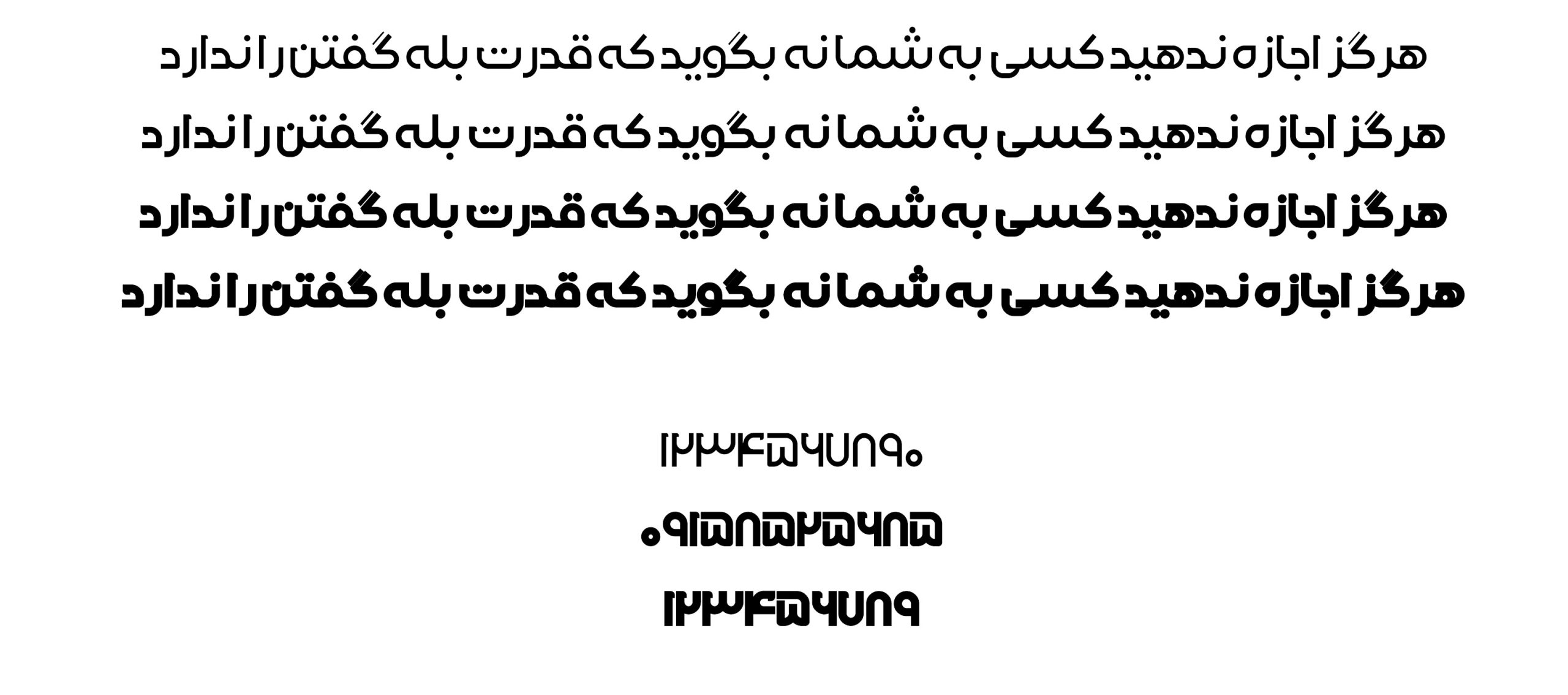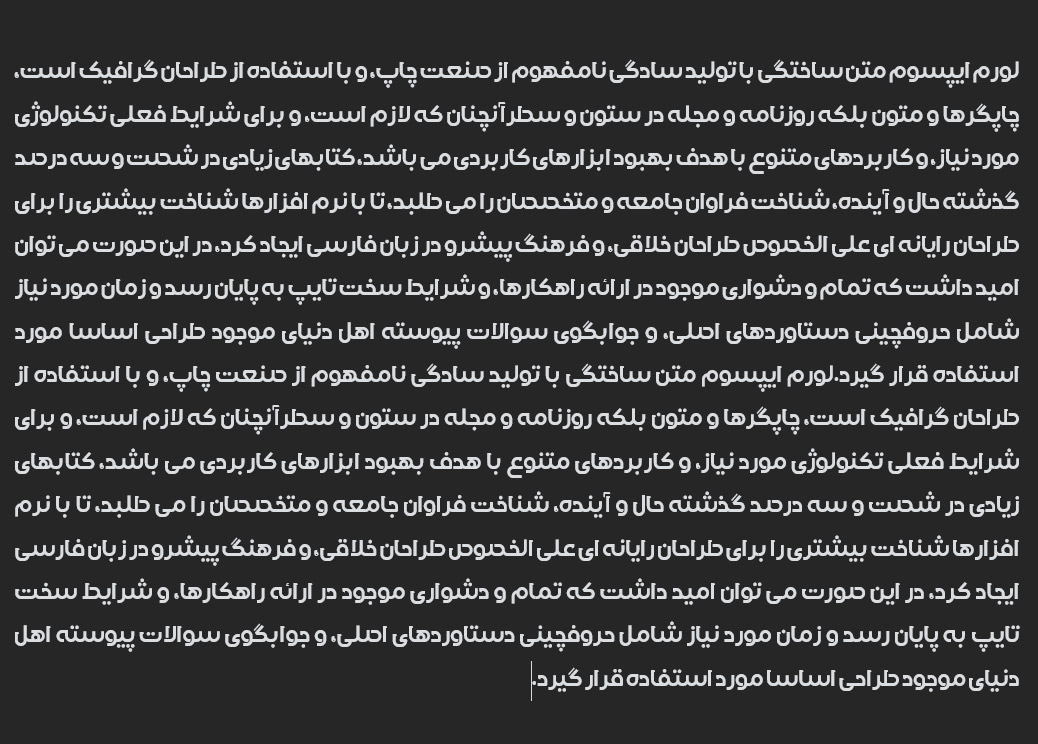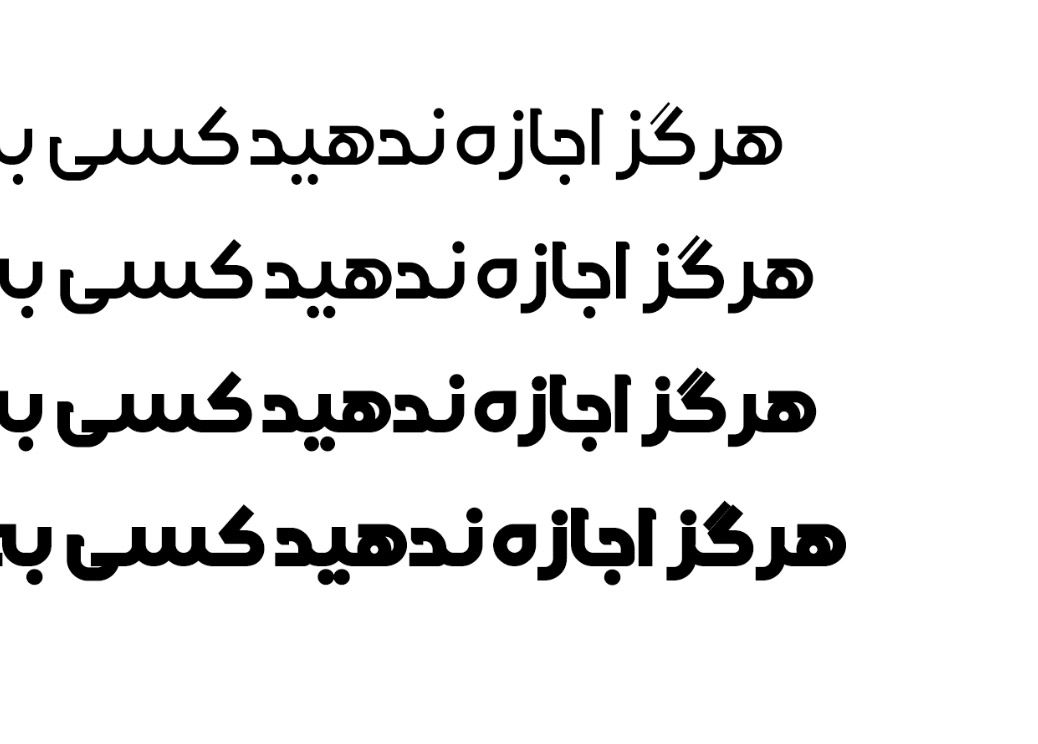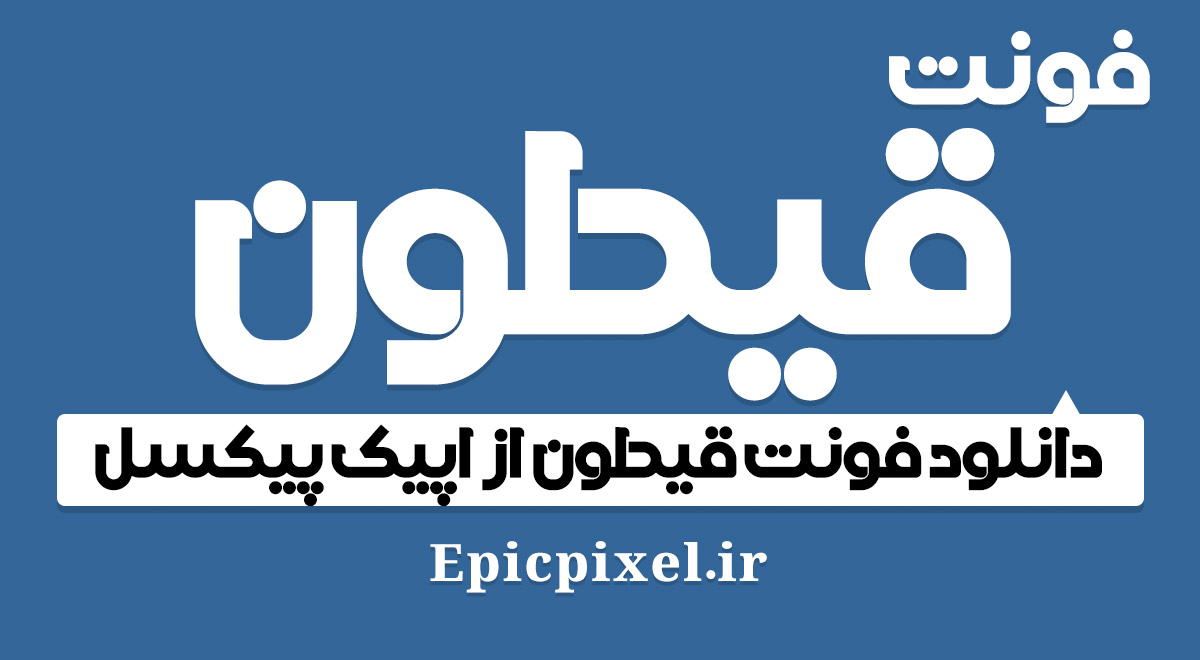
4 فونت قیطون فارسی
| ⭐ توضیحات | مجموعه ای کامل از فونت های قیطون و نسخه شبیه سازی شده اپیک قیطون فونت اپیک قیطون با پشتیبانی از حروف فارسی ، اعداد فارسی Fu Num بهمراه نسخه وب |
فونت قیطون زیبایی و ظرافت در دنیای نوشتن
در دنیای طراحی و گرافیک، فونتها بهعنوان ابزارهای قدرتمندی برای انتقال پیام و ایجاد حس و حال خاص شناخته میشوند. انتخاب فونت مناسب میتواند تأثیر بسزایی بر زیبایی و خوانایی متن داشته باشد. فونت قیطون یکی از فونتهای فارسی محبوب و پرکاربرد است که با ظرافت و زیبایی خود، جایگاه ویژهای در بین طراحان و گرافیستها پیدا کرده است.
تاریخچه فونت قیطون
فونت قیطون در سال ۱۳۸۶ توسط گروه طراحی قلم فارسی طراحی و منتشر شد. این فونت با الهام از هنر خوشنویسی ایرانی و با هدف ایجاد یک فونت زیبا و خوانا برای متون فارسی شکل گرفت. از زمان انتشار، فونت قیطون بهسرعت مورد استقبال طراحان و گرافیستها قرار گرفت و به یکی از پرکاربردترین فونتهای فارسی تبدیل شد.
ویژگیهای فنی فونت قیطون
کاربردهای فونت قیطون
فونت قیطون بهدلیل زیبایی و ظرافت خود، کاربردهای فراوانی در زمینههای مختلف دارد. از جمله کاربردهای این فونت میتوان به موارد زیر اشاره کرد:
دانلودطراحی گرافیک: فونت قیطون بهطور گسترده در طراحی لوگو، پوستر، کارت ویزیت، بروشور و سایر محصولات چاپی استفاده میشود.
وبسایتها و اپلیکیشنها: فونت قیطون بهدلیل خوانایی و زیبایی خود، انتخاب مناسبی برای طراحی وبسایتها و اپلیکیشنهای فارسی است.
متون چاپی: فونت قیطون بهدلیل خوانایی و زیبایی خود، انتخاب مناسبی برای چاپ کتاب، مجله، روزنامه و سایر متون چاپی است.
اسناد رسمی و اداری: فونت قیطون بهدلیل رسمیت و اعتبار خود، انتخاب مناسبی برای استفاده در اسناد رسمی و اداری است.
مزایا و معایب استفاده از فونت قیطون
فونت قیطون دارای مزایای زیادی است که از جمله آنها میتوان به موارد زیر اشاره کرد:
خوانایی و سهولت استفاده: فونت قیطون دارای خطوط صاف و واضحی است که باعث میشود خواندن متن با این فونت آسان باشد.
زیبایی و ظرافت ظاهری: فونت قیطون با الهام از هنر خوشنویسی ایرانی طراحی شده است و دارای ظاهری زیبا و ظریف است.
انتقال حس رسمی بودن و اعتبار: فونت قیطون بهدلیل رسمیت و اعتبار خود، انتخاب مناسبی برای استفاده در اسناد رسمی و اداری است.
ایجاد حس ایرانی بودن و اصالت: فونت قیطون با الهام از هنر خوشنویسی ایرانی طراحی شده است و به همین دلیل حس ایرانی بودن و اصالت را منتقل میکند.
با این حال، فونت قیطون دارای معایب جزئی نیز هست که از جمله آنها میتوان به موارد زیر اشاره کرد:
امکان ایجاد خستگی چشم در استفاده طولانیمدت: فونت قیطون دارای خطوط ظریفی است که در استفاده طولانیمدت ممکن است باعث خستگی چشم شود.
محدودیت در استفاده در برخی از سبکهای طراحی: فونت قیطون بهدلیل رسمیت و اعتبار خود، ممکن است برای برخی از سبکهای طراحی مناسب نباشد.
عدم تطابق با برخی از زبانها و خطوط: فونت قیطون ممکن است با برخی از زبانها و خطوط دیگر سازگار نباشد.
مقایسه فونت قیطون با سایر فونتهای مشابه
فونت قیطون با فونتهای فارسی دیگری مانند فونت ایران سنس، فونت نستعلیق و فونت وان قابل مقایسه است. این فونتها نیز دارای ویژگیهای زیبایی و ظرافت هستند، اما هر کدام ویژگیهای منحصربهفرد خود را دارند.
آینده فونت قیطون
فونت قیطون یکی از محبوبترین فونتهای فارسی است و به نظر میرسد که جایگاه خود را در دنیای طراحی و گرافیک حفظ خواهد کرد. در آینده، ممکن است شاهد پیشرفتها و تغییراتی در فونت قیطون باشیم، اما بهطور کلی این فونت همچنان بهعنوان یک فونت محبوب و پرکاربرد باقی خواهد ماند.
فونت قیطون یک فونت زیبا و ظریف است که دارای کاربردهای فراوانی در زمینههای مختلف است. این فونت بهدلیل خوانایی، زیبایی و رسمیت خود، انتخاب مناسبی برای استفاده در پروژههای مختلف است.
3. فونت قیطون برای چه نوع پروژههایی مناسب است؟
دانلودفونت قیطون برای انواع پروژههای طراحی گرافیک و نوشتاری مناسب است. از جمله کاربردهای این فونت میتوان به موارد زیر اشاره کرد:
طراحی لوگو، پوستر، کارت ویزیت، بروشور و سایر محصولات چاپی
5. آیا فونت قیطون در نسخههای آینده بهروزرسانی خواهد شد؟
بله، احتمال دارد که فونت قیطون در نسخههای آینده بهروزرسانی شود. این بهروزرسانیها ممکن است شامل ویژگیهای جدید، بهبود عملکرد و رفع اشکالات باشد.
جمعبندی
فونت قیطون یک فونت زیبا و ظریف است که دارای کاربردهای فراوانی در زمینههای مختلف است. این فونت بهدلیل خوانایی، زیبایی و رسمیت خود، انتخاب مناسبی برای استفاده در پروژههای مختلف است. با توجه به محبوبیت و کاربرد گسترده این فونت، به نظر میرسد که جایگاه خود را در دنیای طراحی و گرافیک حفظ خواهد کرد.